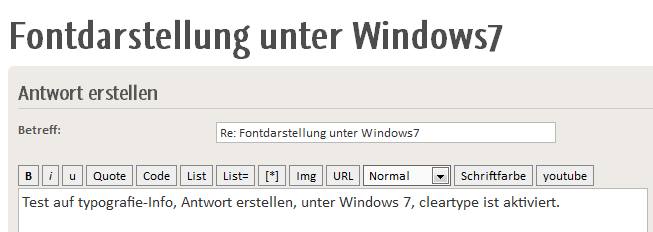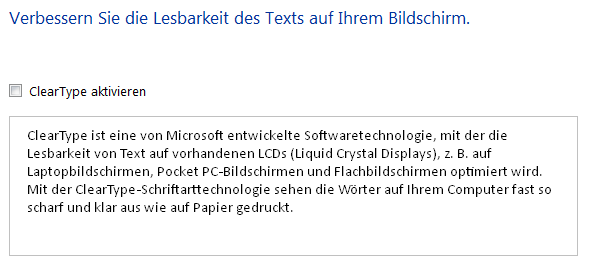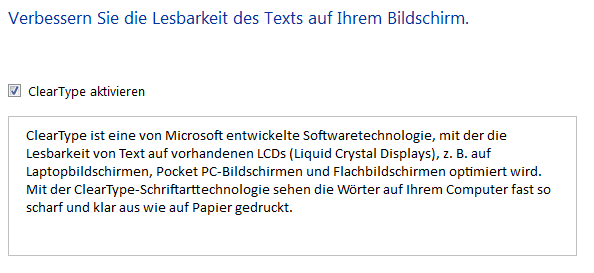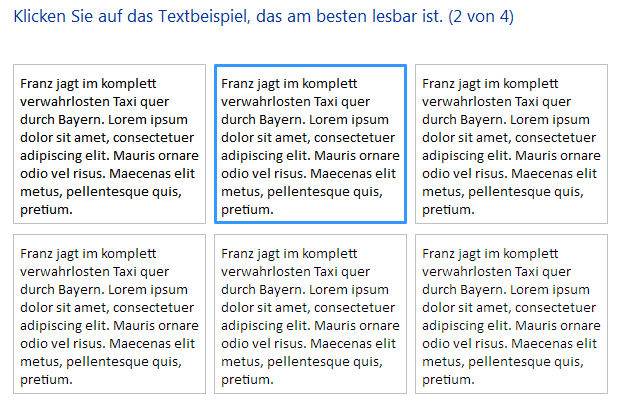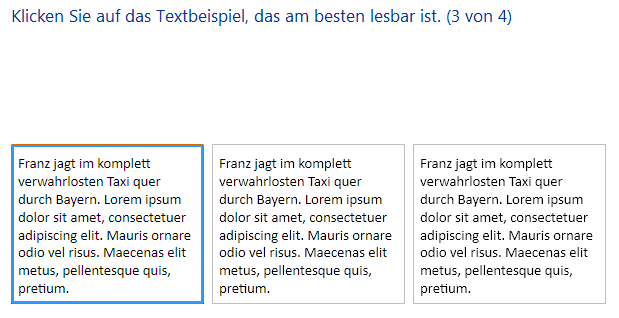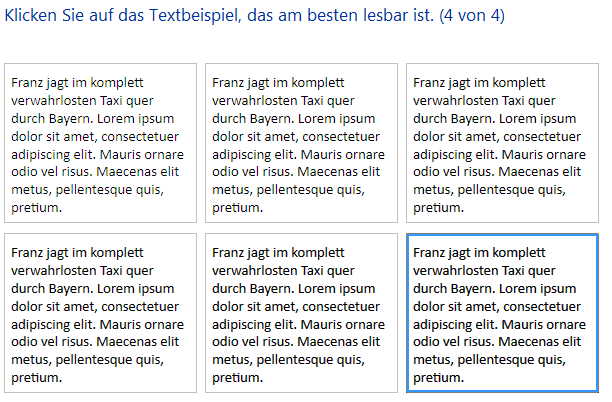
Fontdarstellung unter Windows7
Beim Screenshot aus eurem Editor sind die gleichen Buchstaben unterschiedlich groß und die Kanten haben bei genauerem hinschauen einen Buntstich...
Wo siehst Du denn bei dem Bild einen Buntstich? Ich seh da nur Graustufen an den Kanten.
Da mag es nicht so viel sein, aber schau Dir mal die beiden ersten Screenshots an, in der Vergrößerung sieht man es...
Bei mir sind unter XP folgende Einstellungen aktiv:
Kantenglättung an, Methode "Standard"...
Ist dass das wo man zwischen verschiedenen Test-Texten auswählen kann? Das hatte ich bei Win7 damals auch durch, und habe das Schriftbild auch nicht so wie bei XP hinbekommen...
Natürlich würde ich mich auch über Monitore freuen die anstatt immer größer zu werden wesentlich dichtere Pixel hätten. Also statt irgendwas um die 96 ppi besser 240 ppi. Natürlich müsten dem entsprechend auch alle Betriebssysteme dieser Welt dann sämtliche GUI Elemente als Vektorgrafiken vorliegen haben und entsprechend dem Monitor die Elemente in der benötigten Auflösung rastern.
Die allerneusten Labor E-Reader Displays geben Anlaß zur Hoffnung, in 5 bis 10 Jahren könnte es soweit sein. :-)
Als Programmierer must Du sehen wo Du am besten arbeiten kannst. Vorschlag: Benutze eine virtuelle Maschine auf der Du programmierst. Virtual Box von Sun ist sehr schlank und kostenfrei. Damit kannst Du dann XP auch auf matschigen, unscharfen aber zeitgemäßen Betriebssystemen laufen lassen.
ps. Ich vermute das "matschige" Fontrendering wird dann als besonders unangenehm empfunden, wenn das persönliche Sehvermögen außergewöhnlich (120% und mehr) gut bzw. aufs scharf sehen trainiert ist. Es ist wie mit einer neuen Brille, ein gewisse Gewöhnungsleistung muß erbracht werden.
so, jetzt mal getestet unter Windows 7:
Das Notebook ist ein Lenovo R500 meines Bruders, die folgenden Einstellugen sind meines Erachtens an seinem Gerät optimal (hier am Eizo-Bildschirm würde ich andere Einstellungen wählen):
Cleartype bewusst deaktiviert --> Graustufenglättung, die aber mit Cleartype-Schriften schlecht aussieht (das ist genau das, was du uns gezeigt hast bei deinem Screenshot - auch hier sind manche Zeichen dicker und größer als andere - die Schrift ist nicht auf Graustufen-Glättung ausgelegt):
das selbe mit aktiviertem Standard-Cleartype:
im folgenden 3 Optimierungsstufen (wie gesagt, sieht das am Lenovo-Bildschirm gut aus, hier am Eizo würde ich in Details andere Varianten wählen - speziell im letzten Schritt):
Und hier noch ein Screenshot vom Forum, allerdings vor der manuellen Optimierung gemacht - allerdings mit Cleartype an:
Warum verschiedene Varianten? TFT-Bildschirme haben verschiedene Techniken und verschiedene Anordnungen der RGB-Elemente (Streifen, gewinkelt, andere Reihenfolge der 3 Elemente, ...) Je nachdem ist die eine oder andere Einstellung besser oder schlechter geeignet. Solange Cleartype an ist, wenn Cleartype-Schriften verwendet werden, sollte man ein annehmbares Ergebnis erreichen.
Warten auf 300dpi :)
Das sind diese Macken, die ich auch hatte. Aber es kann ja nicht sein, das man sich dann zu jedem OS den passenden Monitor kaufen muss.
Irgendwas muss bei Win 7 generell anders sein. Ich tagelang im Netz nach Lösungen gesucht, aber ausprobiert, in den Systemeinstellungen geschaut, die Systemschriftarten ausgewechselt (gibts ein kleines Tool für): Nichts, kein zufriedenstellendes Bild.
Warum musste MS denn alles so umschmeissen? Warum konnte es die Sachen nicht so lassen wir unter XP? Selbst als ich auf meinem Notebook anfänglich Vista drauf hatte traten die Probleme nicht auf, auch nicht auf dem Notebook meiner Frau, mit Win 7 wohl...
MS muss doch bekannt sein dass diese Form auf vielen Monitoren sch... ausschaut und kein vernünftiges Ergebnis bringt...
Irgendwas muss bei Win 7 generell anders sein.
Neien! Wie oft sollen wir es denn noch sagen!? Die Diskussion dreht sich im Kreise …
Entweder freundest du dich mit ClearType an und wählst die passenden Einstellungen dafür. (Sebastians Screenshots zeigen, wie klar und rattenscharf die ClearType-Fonts unter Windows7 erscheinen).
Oder du bleibst eben für immer bei deiner Graustufenglättung – dann solltest du aber am besten alle ClearType-Schriften deaktivieren, weil das Schriftbild sonst matschig und fleckig sein wird.
Das sind diese Macken, die ich auch hatte. Aber es kann ja nicht sein, das man sich dann zu jedem OS den passenden Monitor kaufen muss.
Nein, musst du eben nicht. Du hast unter Windows 7 mehr Möglichkeiten, das Cleartype-Schriftbild anzupassen, als du unter XP hattest - was ja gut ist, weil es ja eben verschiedene Bildschirme gibt. Aber es ist möglich, dass die Standard-Einstellung nicht zu deinem Bildschirm passt - da kann Microsoft auch nicht zaubern :?
Wenn du aber Cleartype ganz abschaltest, darfst du dich nicht wundern, dass die Cleartype-optimierten Schriften nicht mehr hübsch aussehen.